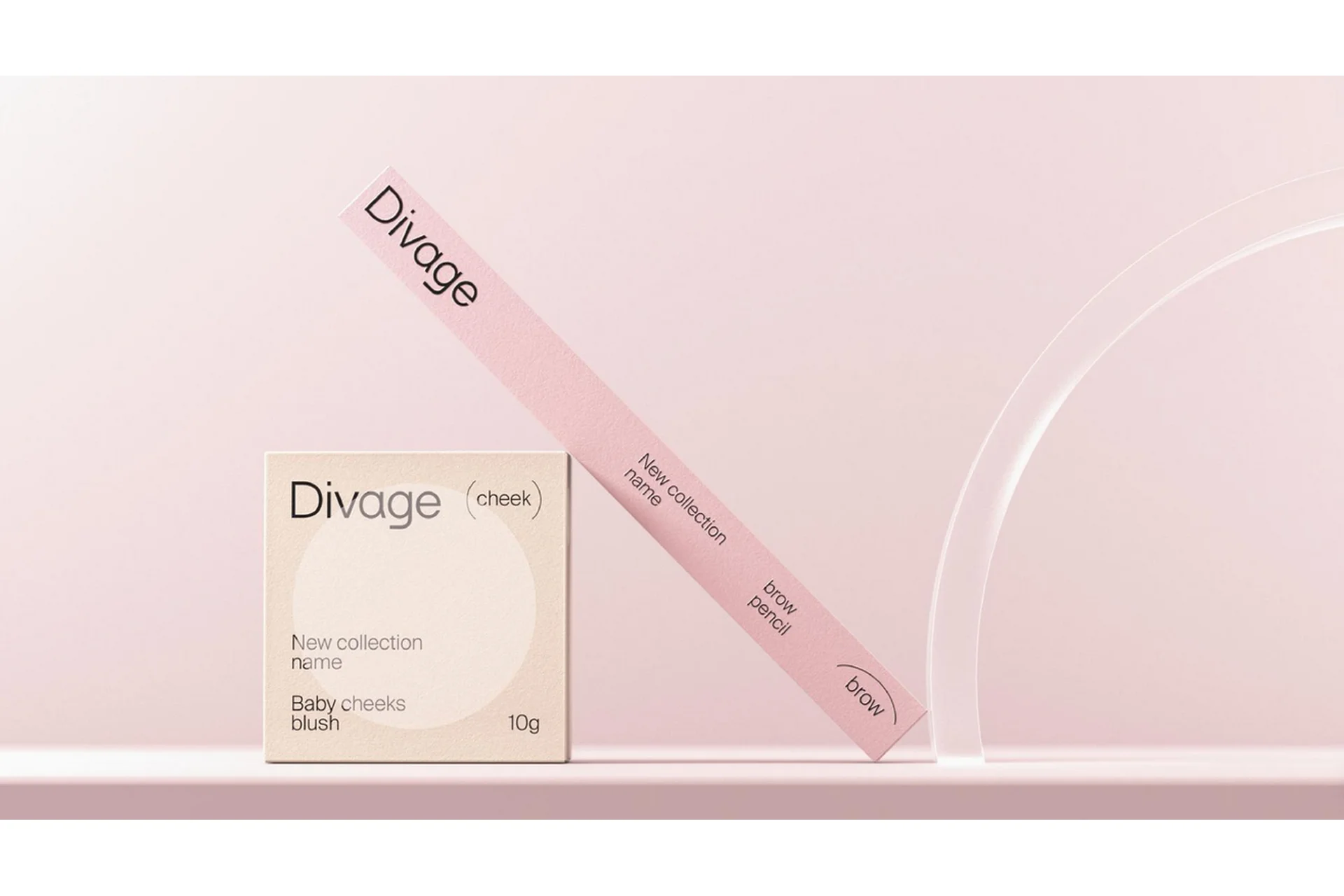
Создание логотипа — процесс, требующий чуткости, эмоциональной связи с брендом и тонкого понимания природы букв. За два занятия вы освоите принципы разработки собственного визуального инструментария и научитесь использовать его в зависимости от запроса клиента. Поймете, как выбирать подходящее графическое решение, наполняя его смыслами. В результате занятий дополните портфолио логотипом, созданным по учебным брифам.
Параметры шрифта
связь письма с современной формой буквы;
пропорции, графема, контраст;
распределение контраста;
взаимосвязи элементов букв;
базовые оптические компенсации.
Логотип
шрифт и логотип, ритм и рифма;
смысловые характеристики;
эмоциональные характеристики;
проработка брифа на создание логотипа.
разбираться в базовых шрифтовых характеристиках;
использовать эти параметры как визуальный инструмент;
защищать выбор своего графического решения перед коллегами и клиентами;
выделять главное в брифе на логотип или айдентику и достигать результатов.